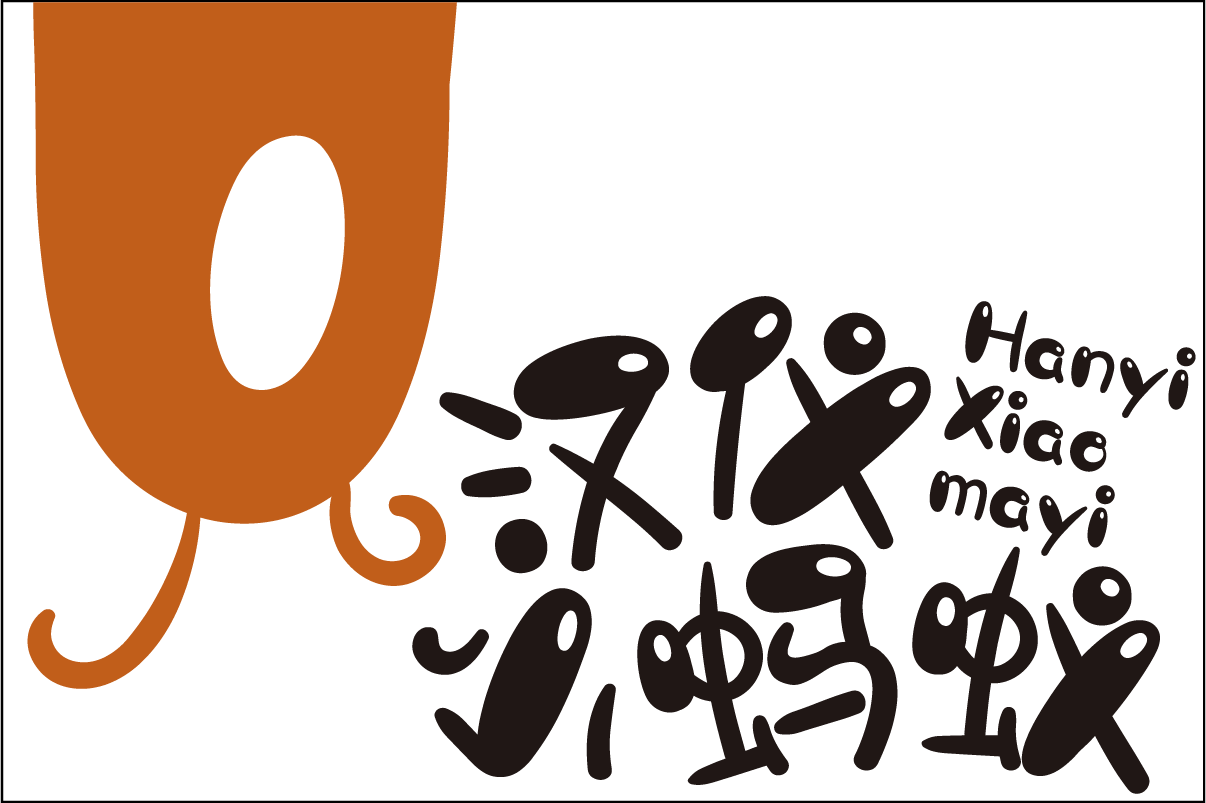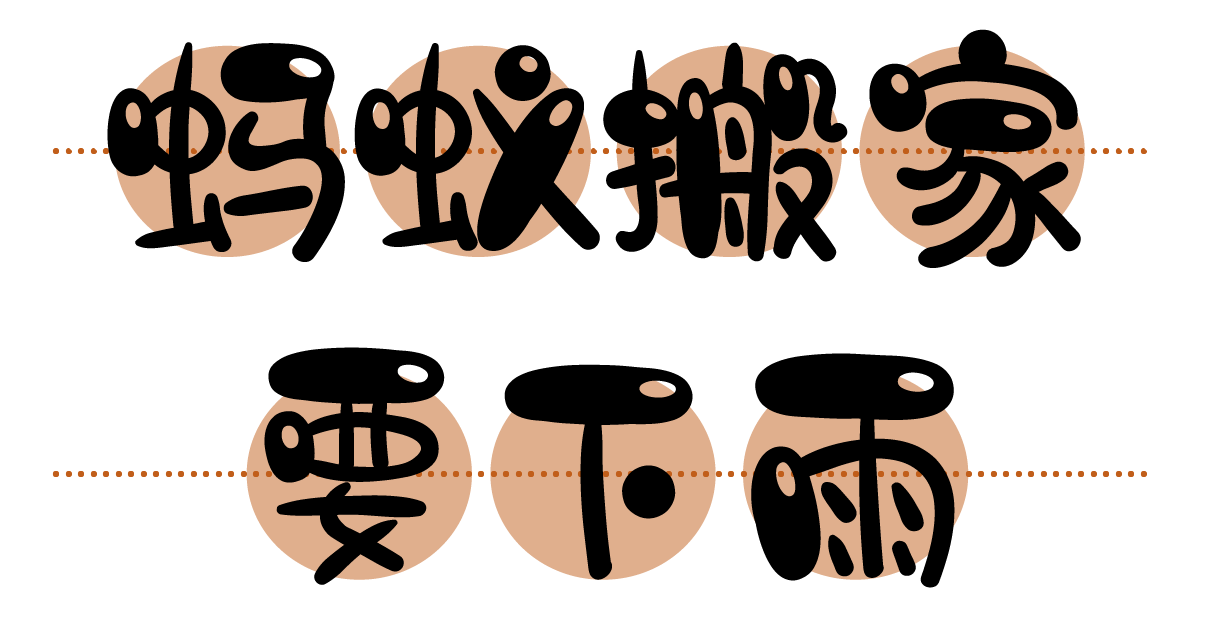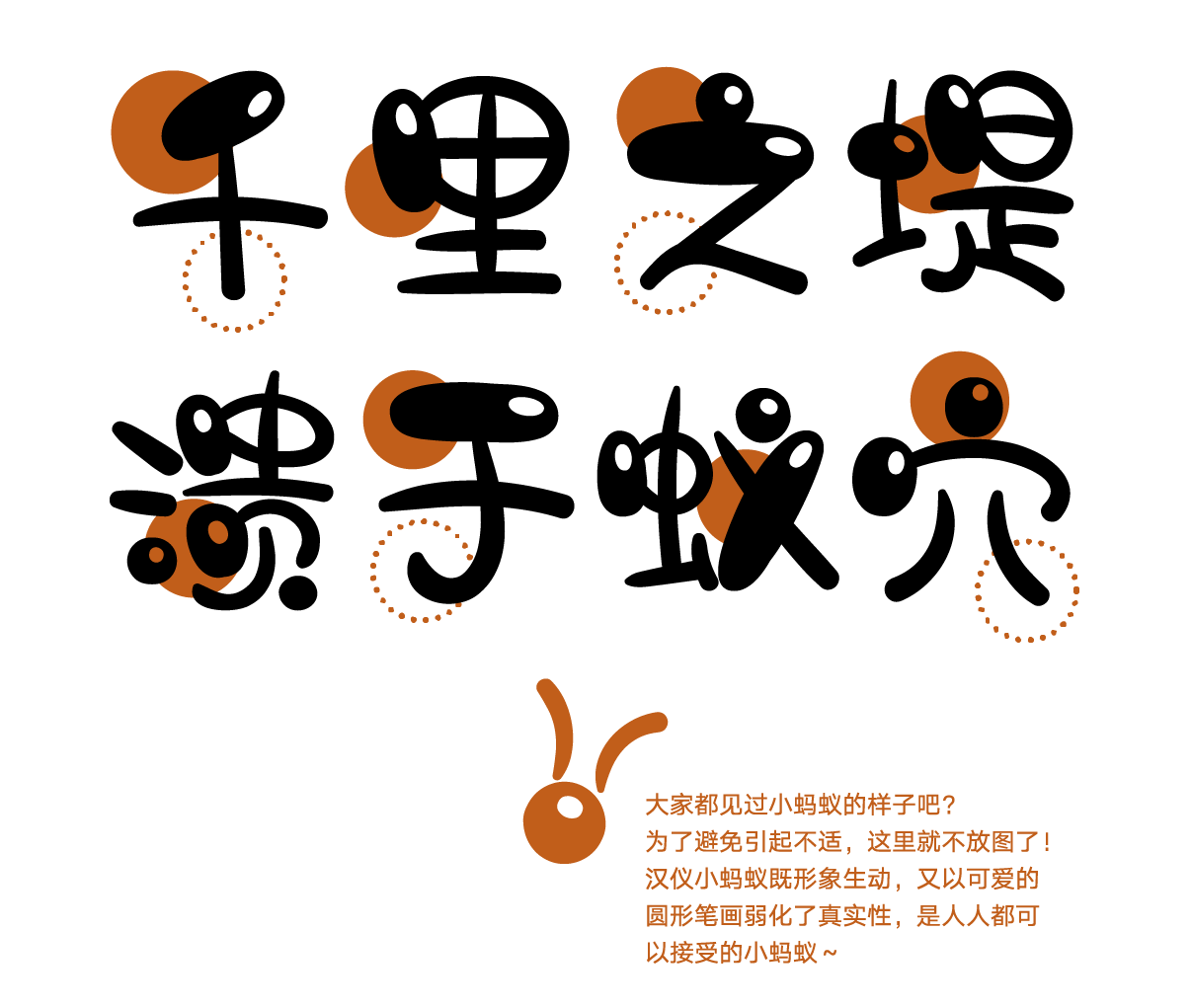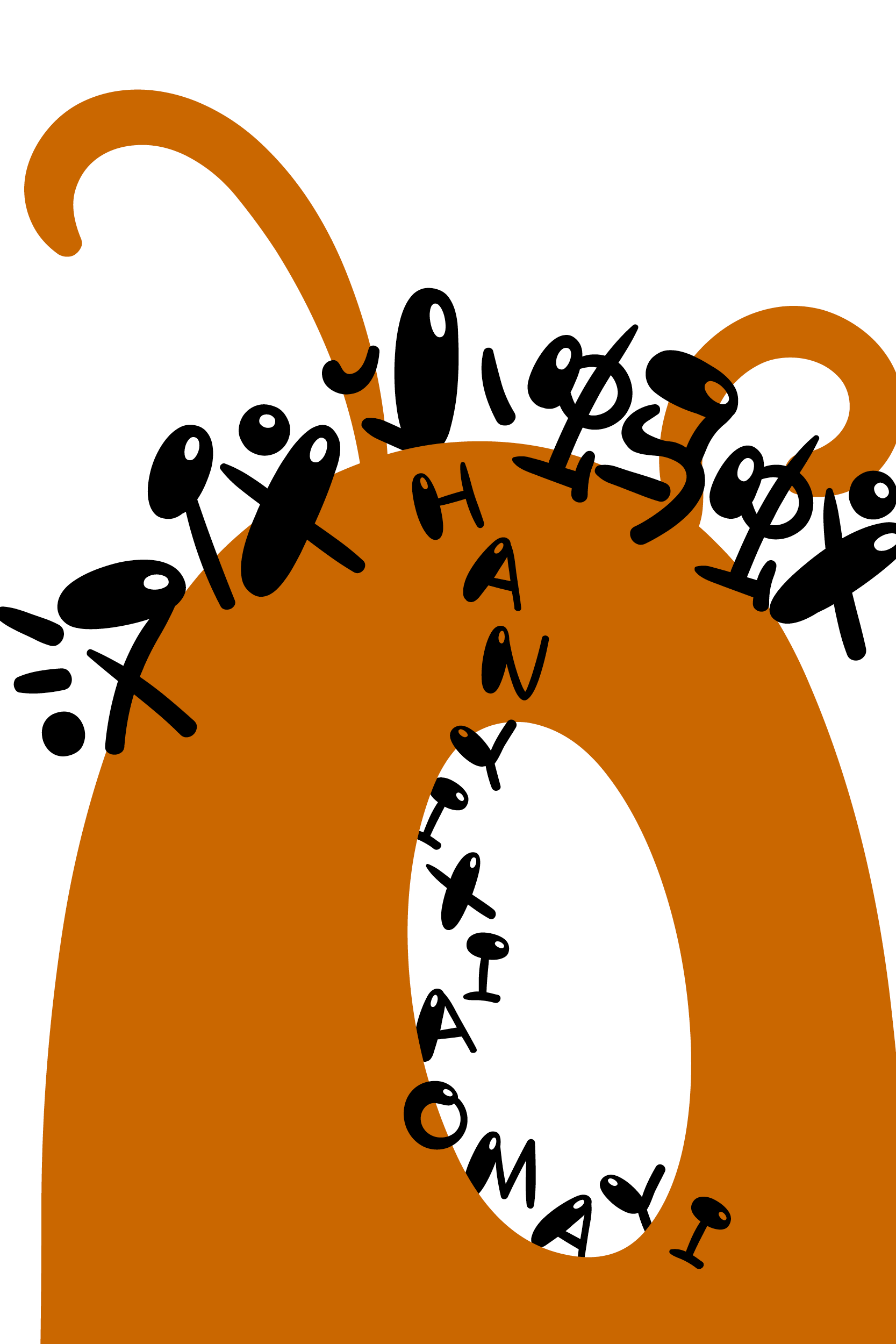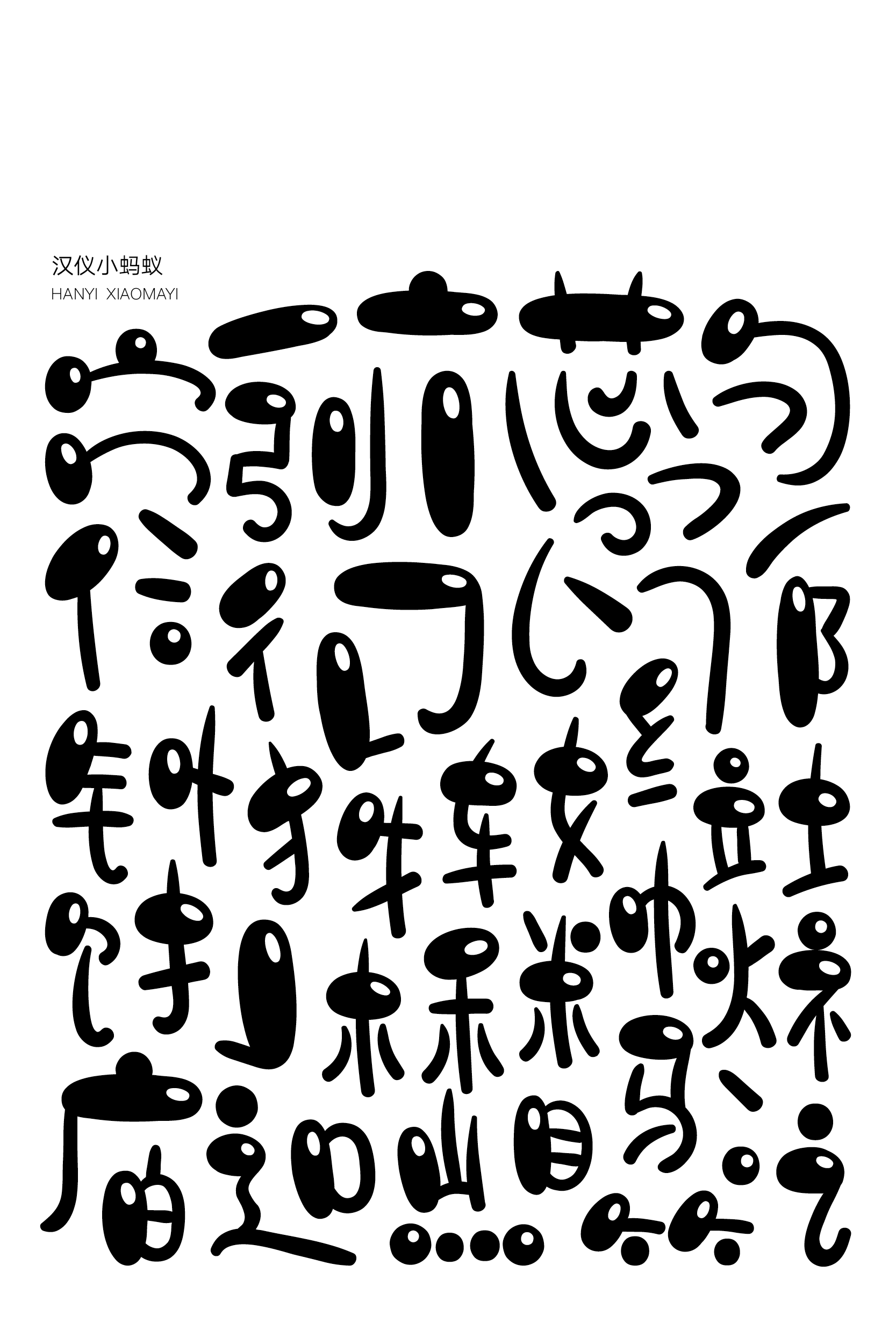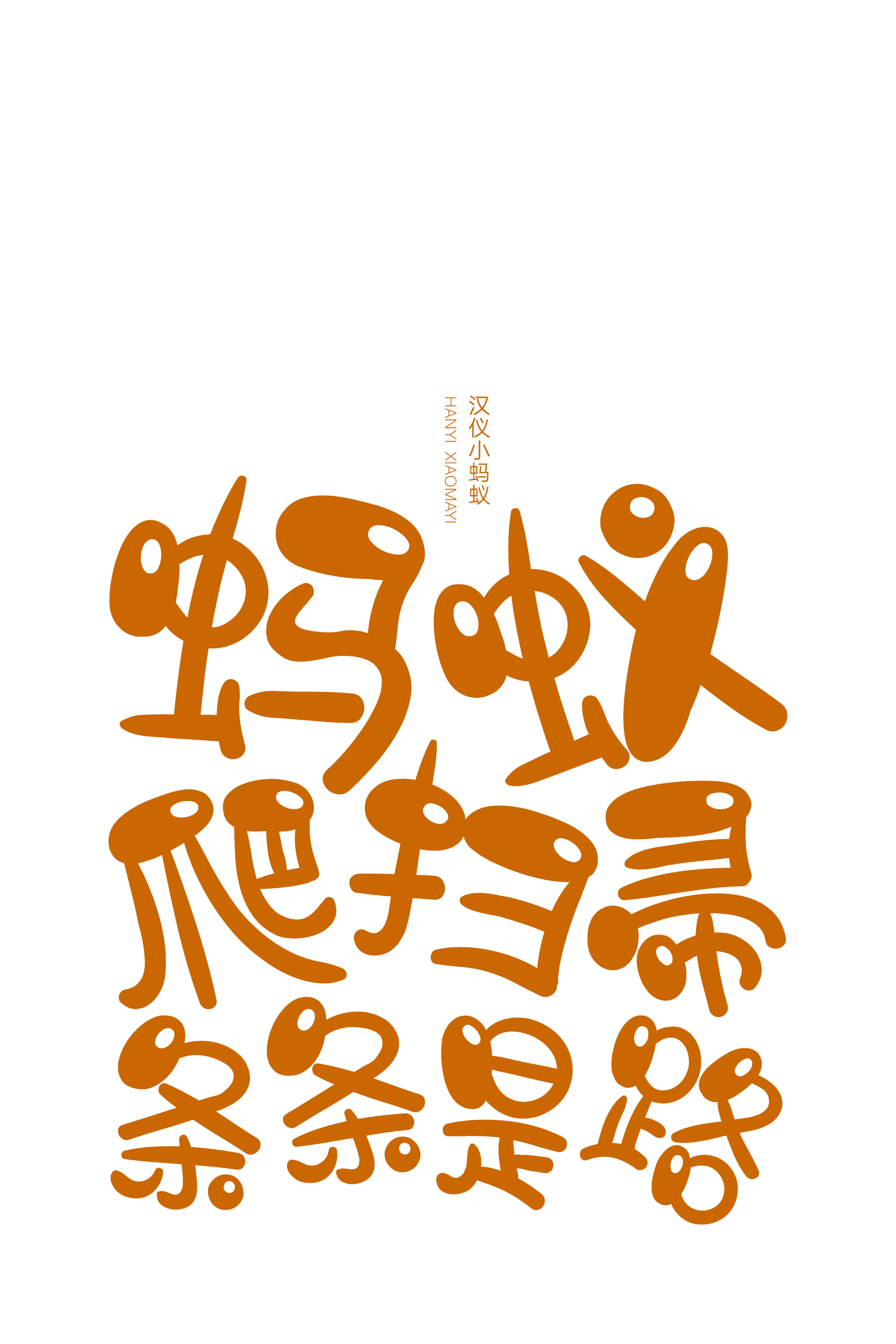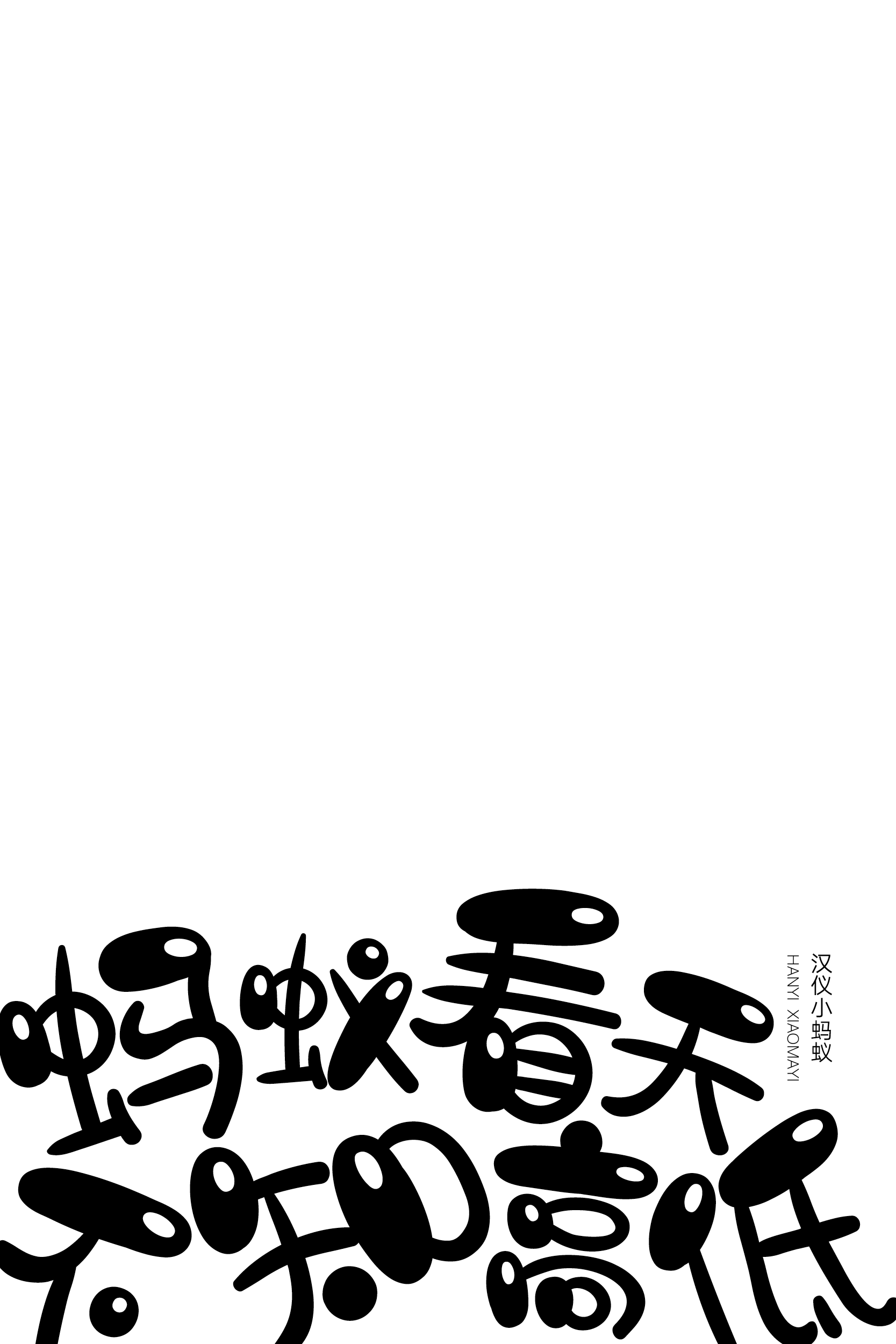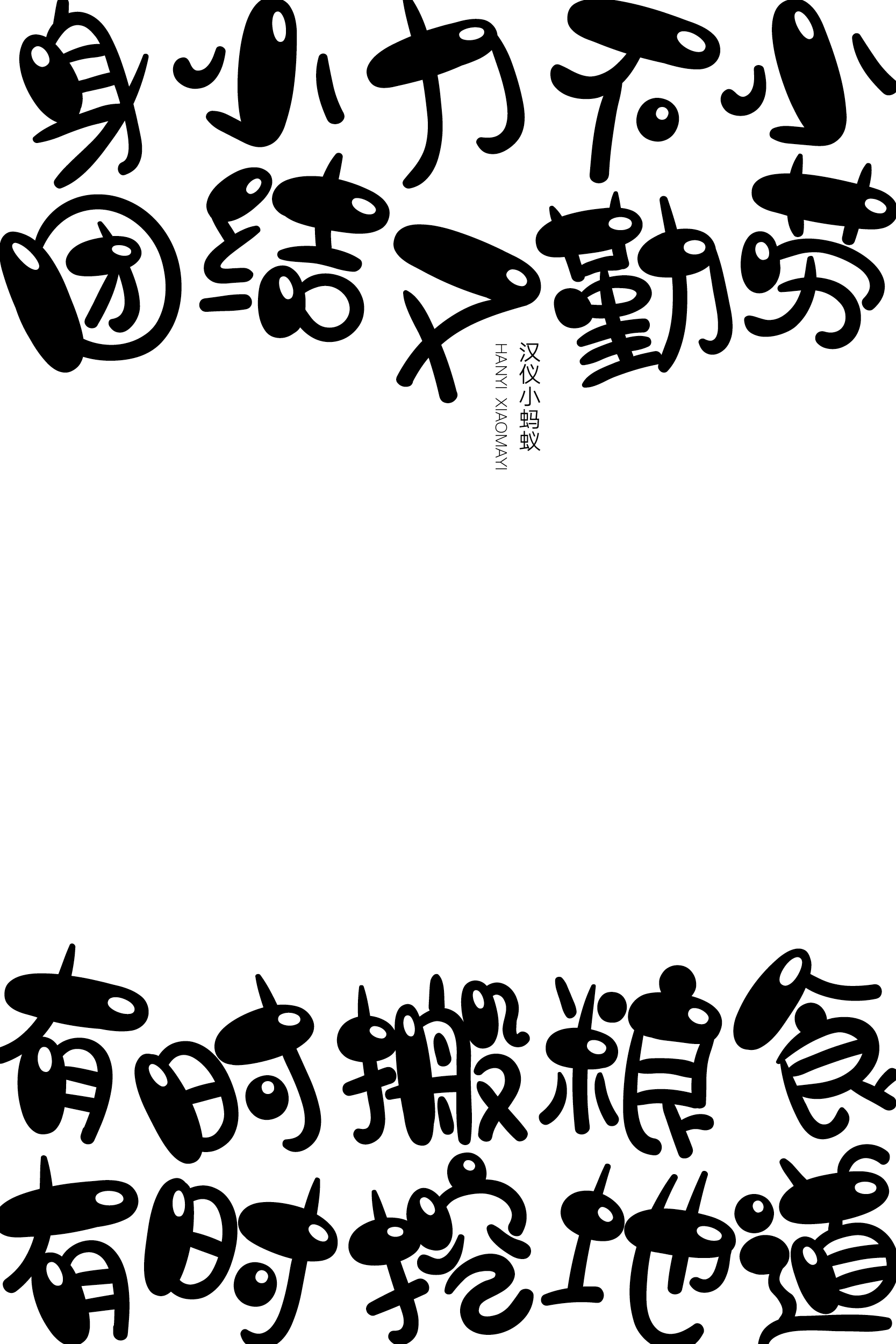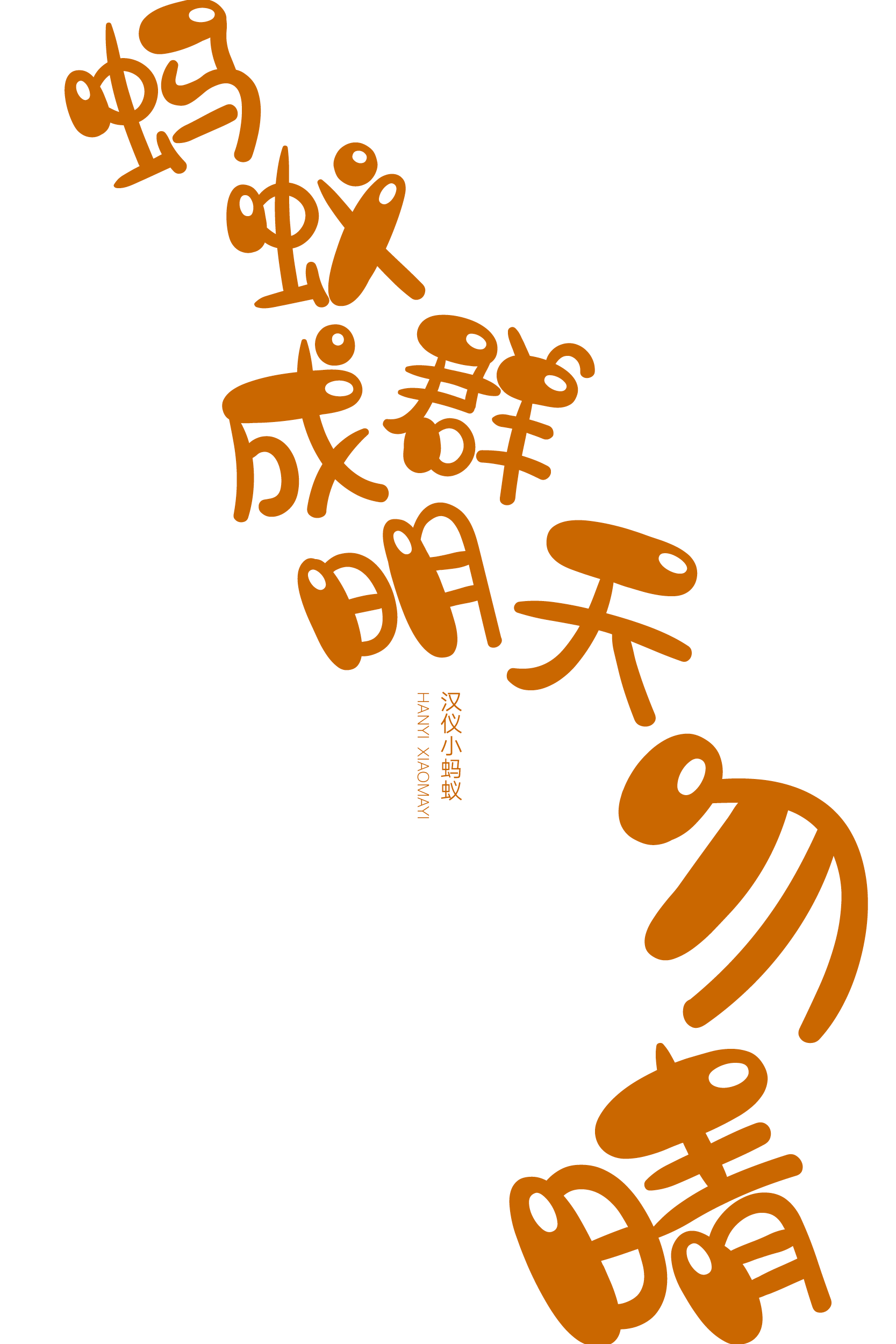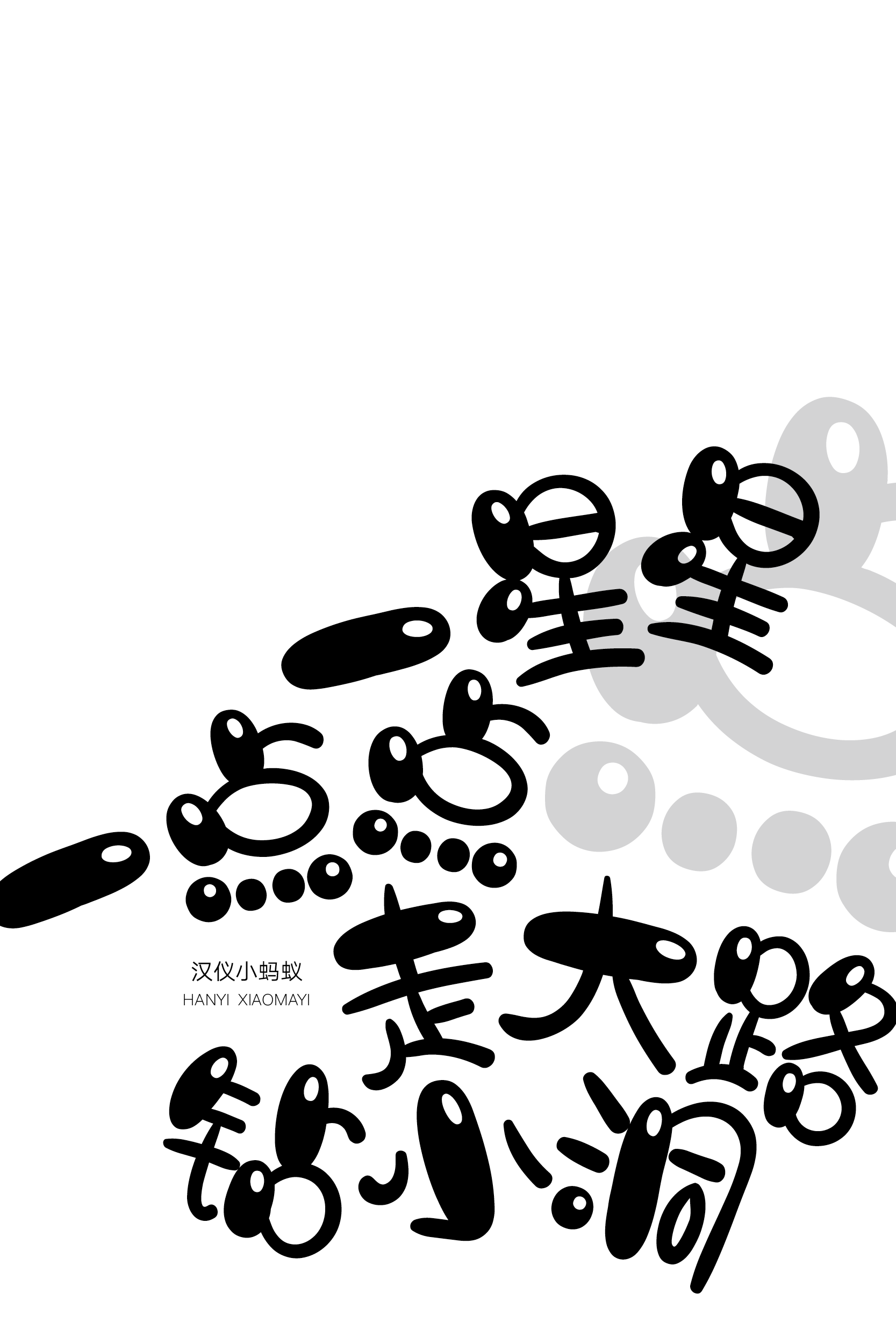
一款适用于少儿科普的绘本字体
趣味 / 稚拙 / 轻松 / 可爱
标志 / 广告 / 包装 / 影视 / 游戏 / 绘本
小蚂蚁,一身亮黑色的盔甲,两根细长的触角,六只有力的足。这样平凡不起眼的小蚂蚁,其实是世界上力气最大的昆虫之一,可以举起比自身重很多倍的东西。它们勤劳,它们团结,它们勇敢。
汉仪小蚂蚁,由笔染工作室创作,将小蚂蚁的形象融入字体设计,生动可爱,憨态可掬。这款字体适合用于少儿科普向的影视动画或绘本读物,也可以用于标识广告、玩具包装等各类使用场景。
字形可爱,结构多变,仿佛正在工作的形态各异的小蚂蚁,栩栩如生。
一行字排列开来,如同蚂蚁成行,让人忍不住蹲下来仔细观察。
粗笔画像蚂蚁的头和腹,饱满又闪闪发光;细笔画或弯或直,弯而像触角,直而像有力的足。
汉仪小蚂蚁的西文部分也如同小蚂蚁的形态,另有风格一致的日文假名、数字及标点符号设计可以满足更丰富的排版应用。